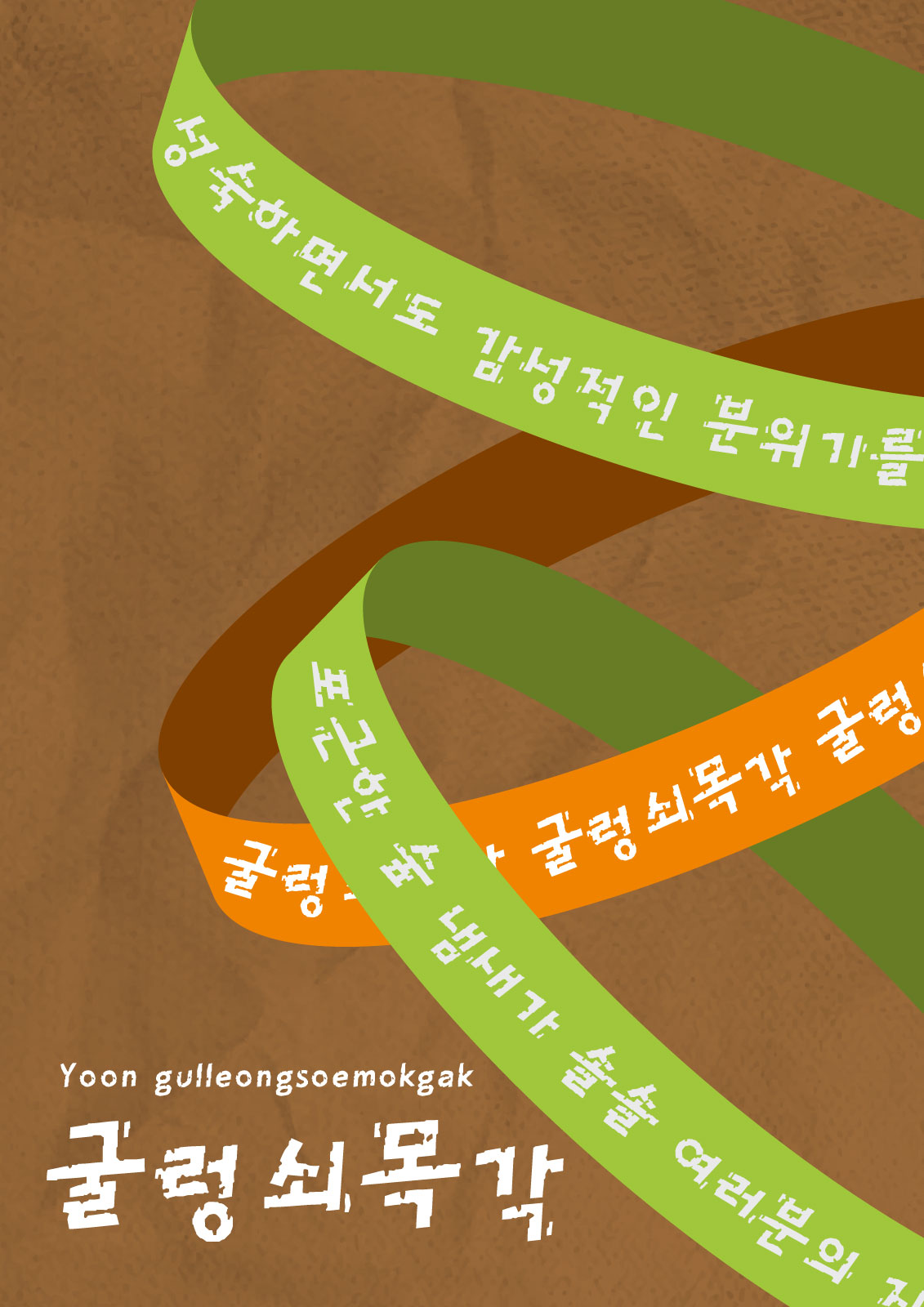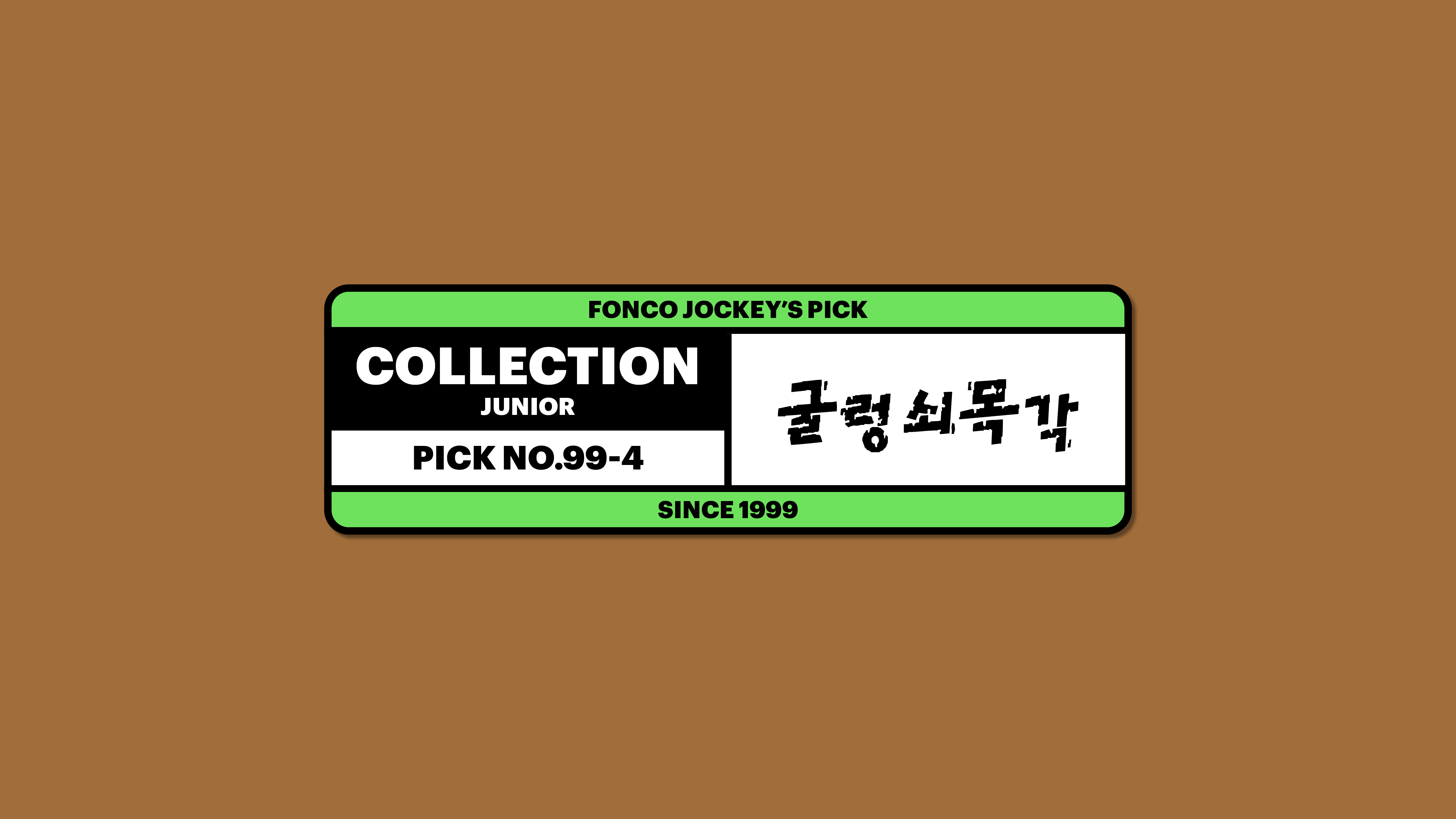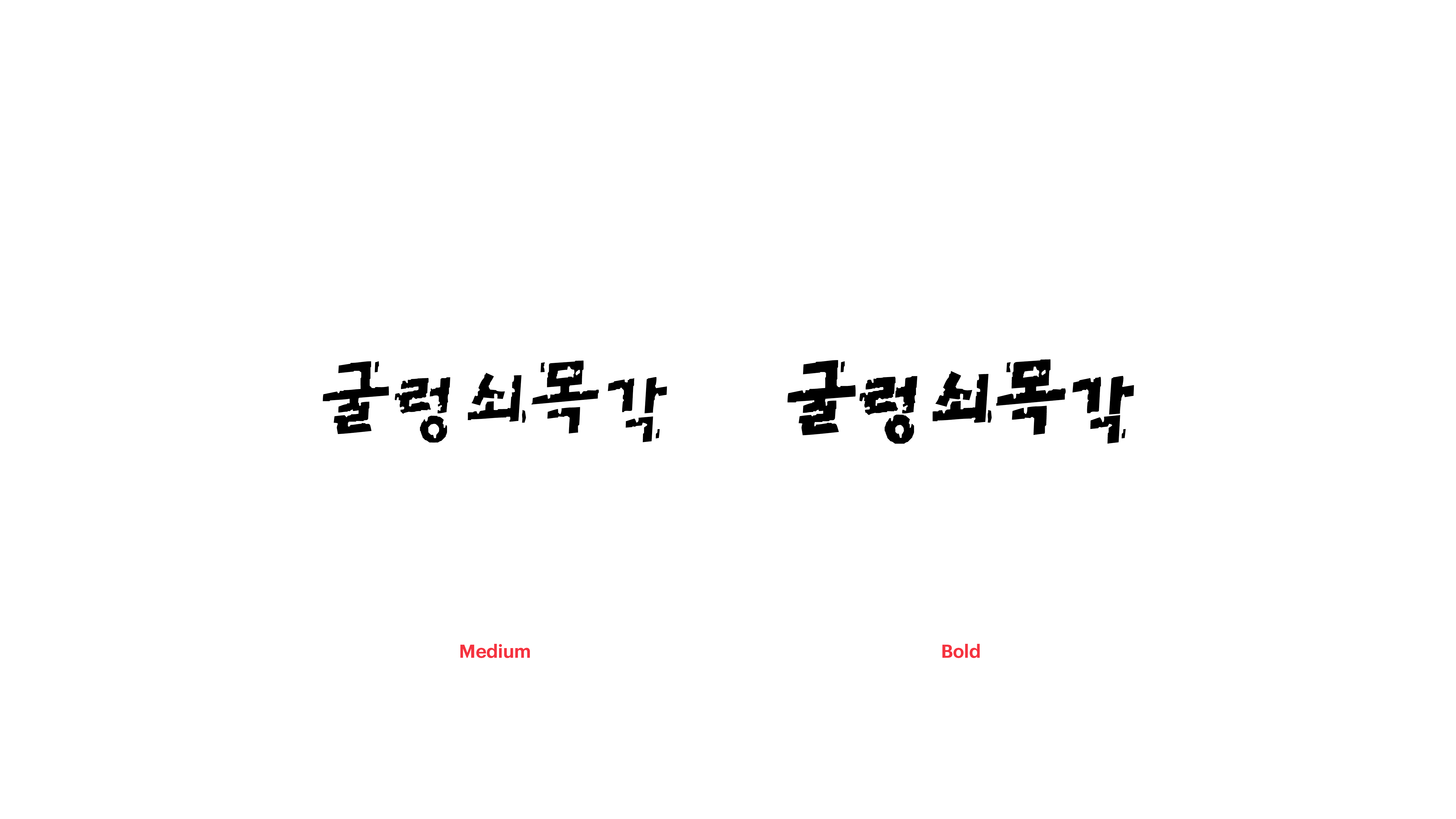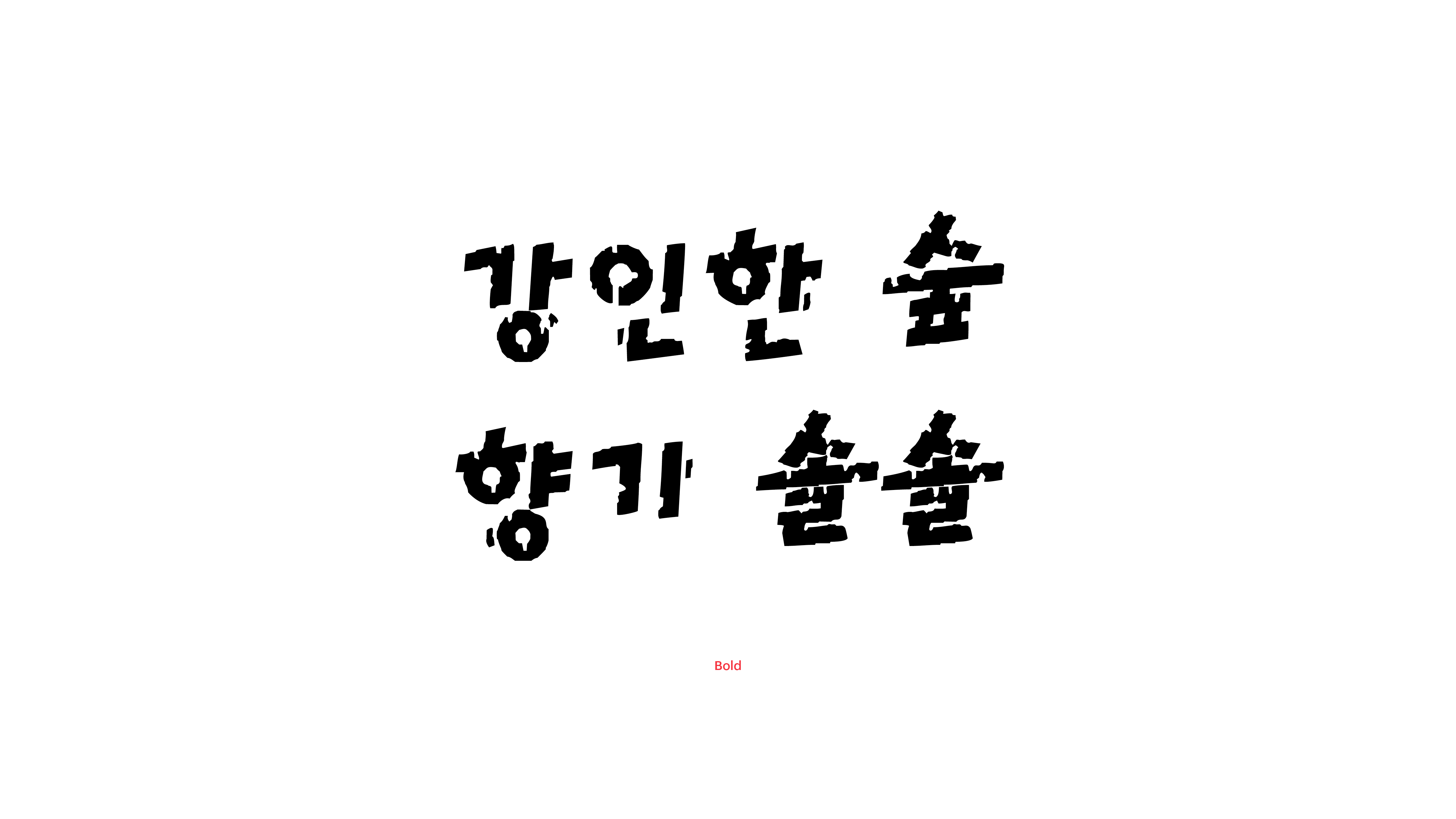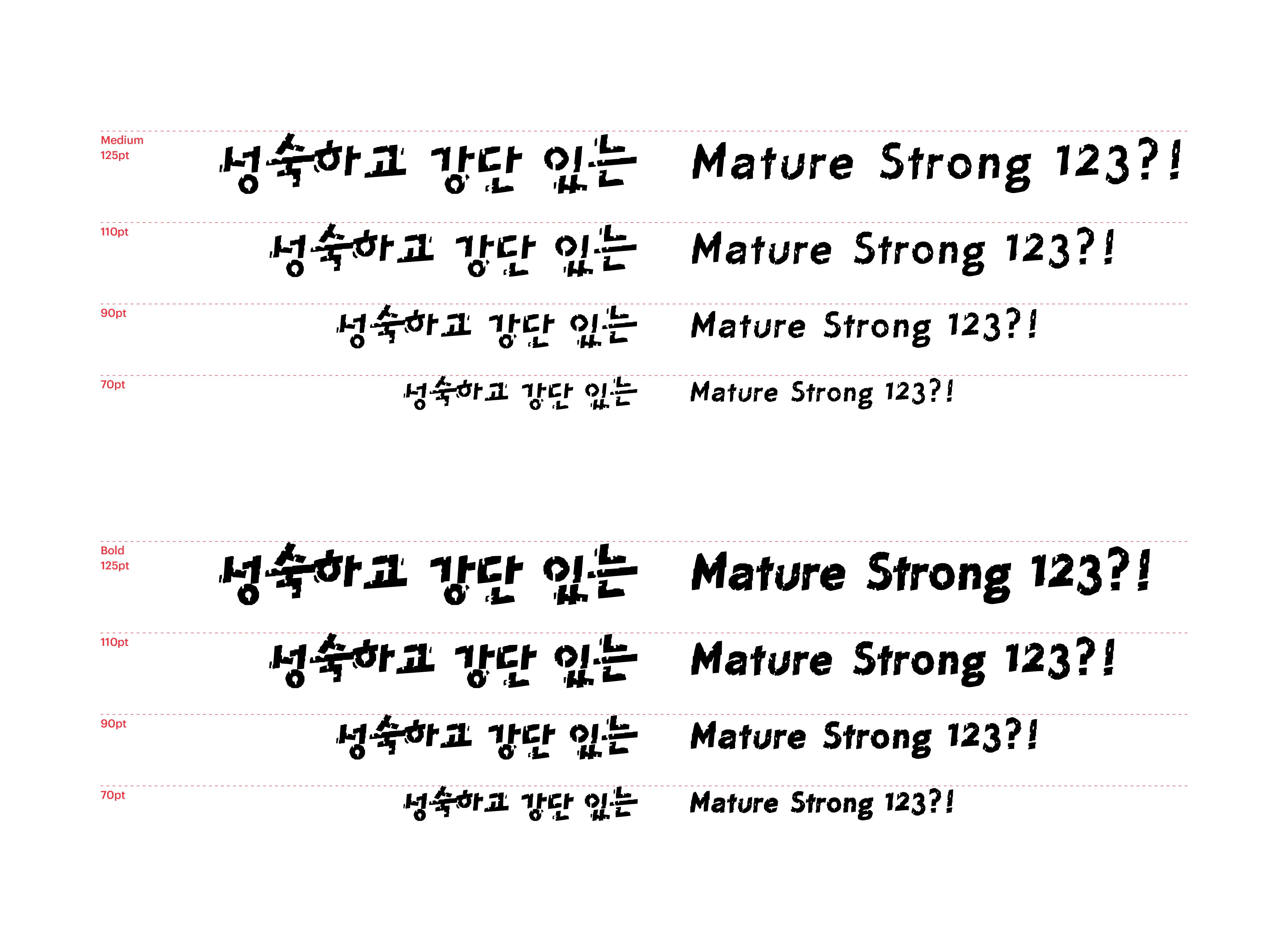
분위기를 180도 바꿀 수 있는 질감의 마법을 느껴보세요. 귀엽고 앙증맞은 굴렁쇠체에 나무를 연상시키는 부드러운 질감을 더하자, 성숙하면서도 감성적인 분위기를 풍기는 굴렁쇠목각체가 탄생하였답니다. 회색빛 건물이 어쩐지 차갑게만 느껴지는 날, 슬쩍 꺼내어 사용해보세요. 포근한 숲 냄새가 솔솔 여러분의 지친 마음을 매만져줄 거예요.
Yoon 굴렁쇠목각